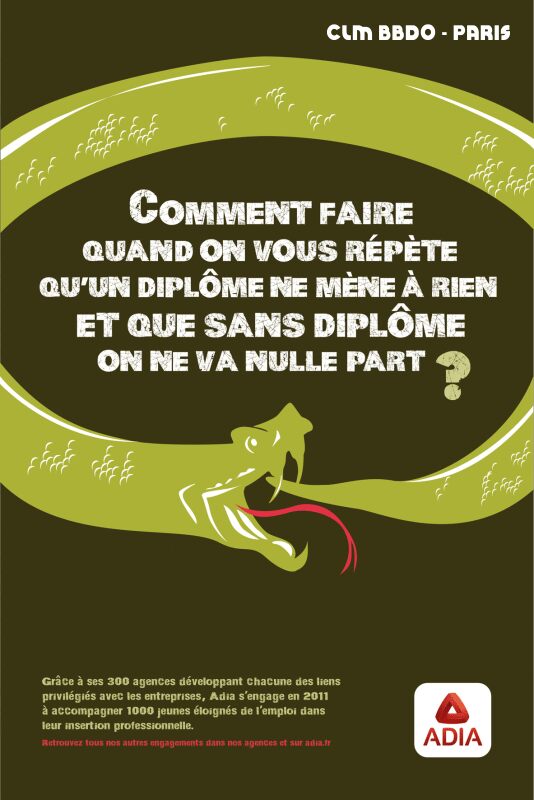
ACTION OF THE TIME
Action of the Time, progettata da Galdino Otten, è un font display eroso e gratuito, costruito da ampie lettere maiuscole a blocco con tagli angolari e spaziatura compatta. La sua erosione è densa e abrasiva.
Come trattamento per titoli in stile distressed, crea l'aspetto di vernice grattata o pellicola screpolata per poster d'azione, copertine di videogiochi e grafiche musicali grintose. La superficie fratturata trova spazio anche nelle aperture di sezioni di riviste e negli articoli editoriali su cultura di strada, sport da combattimento o storia urbana, dove può riecheggiare la grana fotografica, i muri intemperizzati e la segnaletica danneggiata.